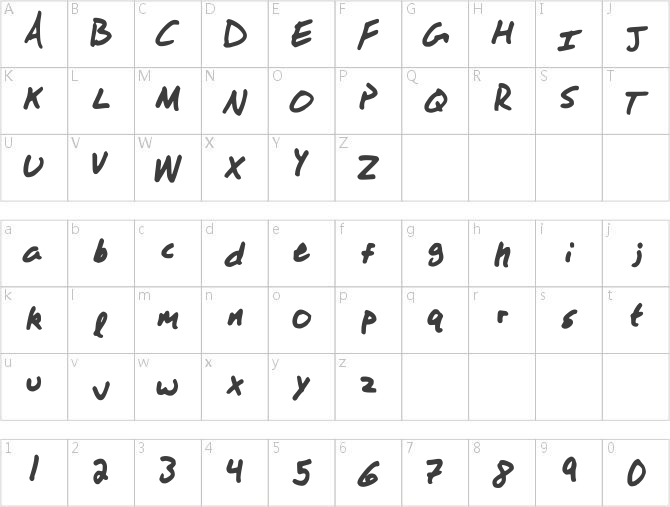
字體名稱: WOAHTha
WOAHThatsBold
WOAHThatsBold介紹
WOAHThatsBold字體字庫是一款讓人賞心悅目、百看不厭的英文字體,適合各類廣告和產(chǎn)品包裝設(shè)計(jì)應(yīng)用,字體大小0.03MB,格式為ttf字體,上傳用戶是lvpyt,作者/版權(quán)方為未知
WOAHThatsBold效果圖